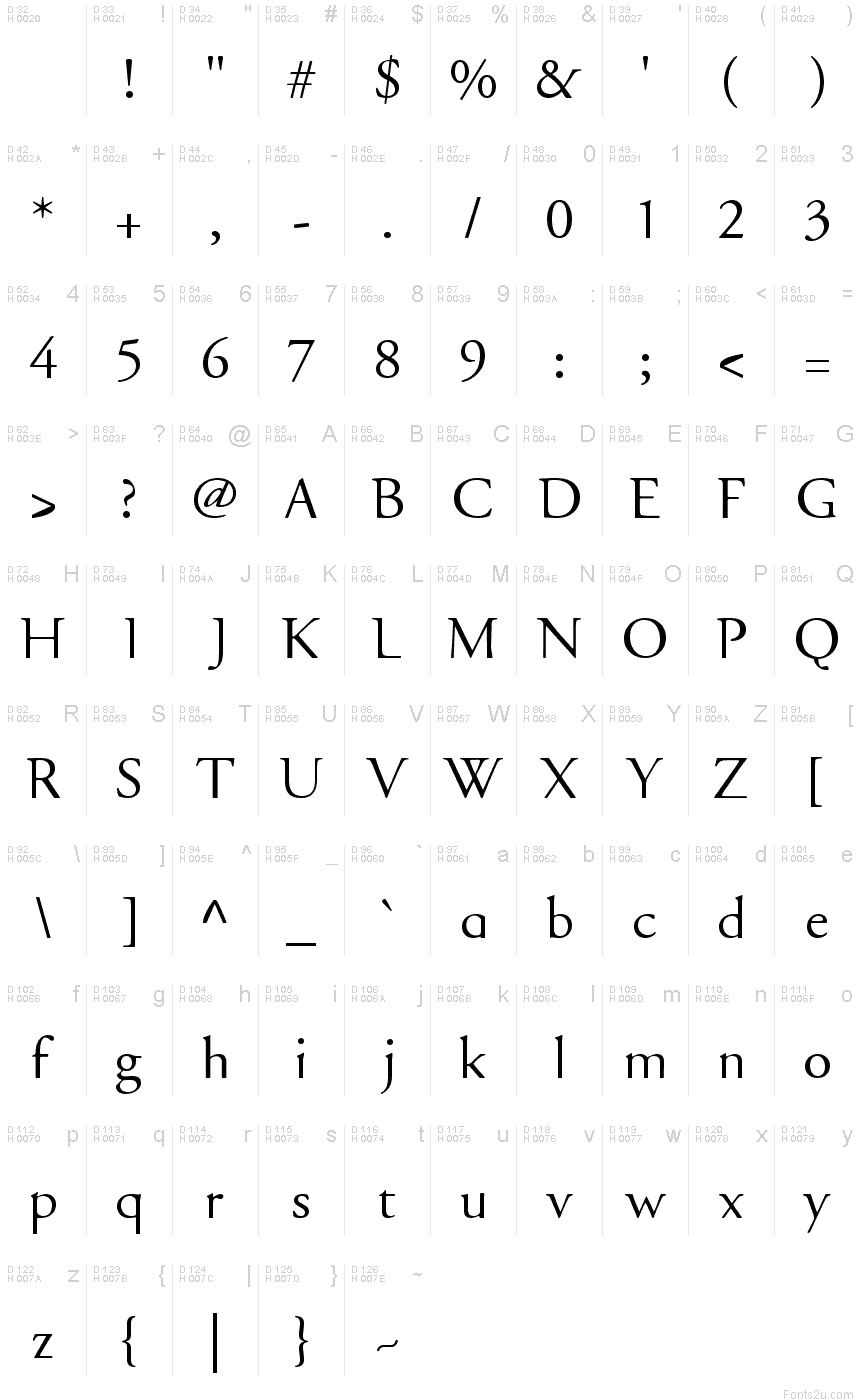
Gara od Iñaki Marquineza to darmowy krój szeryfowy o zachwycającym, książkowym charakterze z nutą drukarskiej czerni. Zaokrąglone formy i wyraziste, nieco nieregularne pociągnięcia nadają każdemu słowu ciepło druku, jakby zostały wyjęte z ulubionej powieści. Szeryfy są solidne, ale nie sztywne, co tworzy delikatny rytm – tekst czyta się lekko, a jednocześnie wygląda oryginalnie zarówno na papierze, jak i na ekranie.
Dzięki Gara tekst staje się bardziej przemyślany i ludzki, co sprawia, że ten darmowy font naturalnie pasuje do okładek książek, magazynów literackich, cytatów, butikowego brandingu, opakowań i układów redakcyjnych. Najlepiej prezentuje się w większych rozmiarach, gdzie jego miękkie krzywizny mogą swobodnie oddychać, i świetnie łączy się z czystym bezszeryfowym krojem w podtytułach lub podpisach.